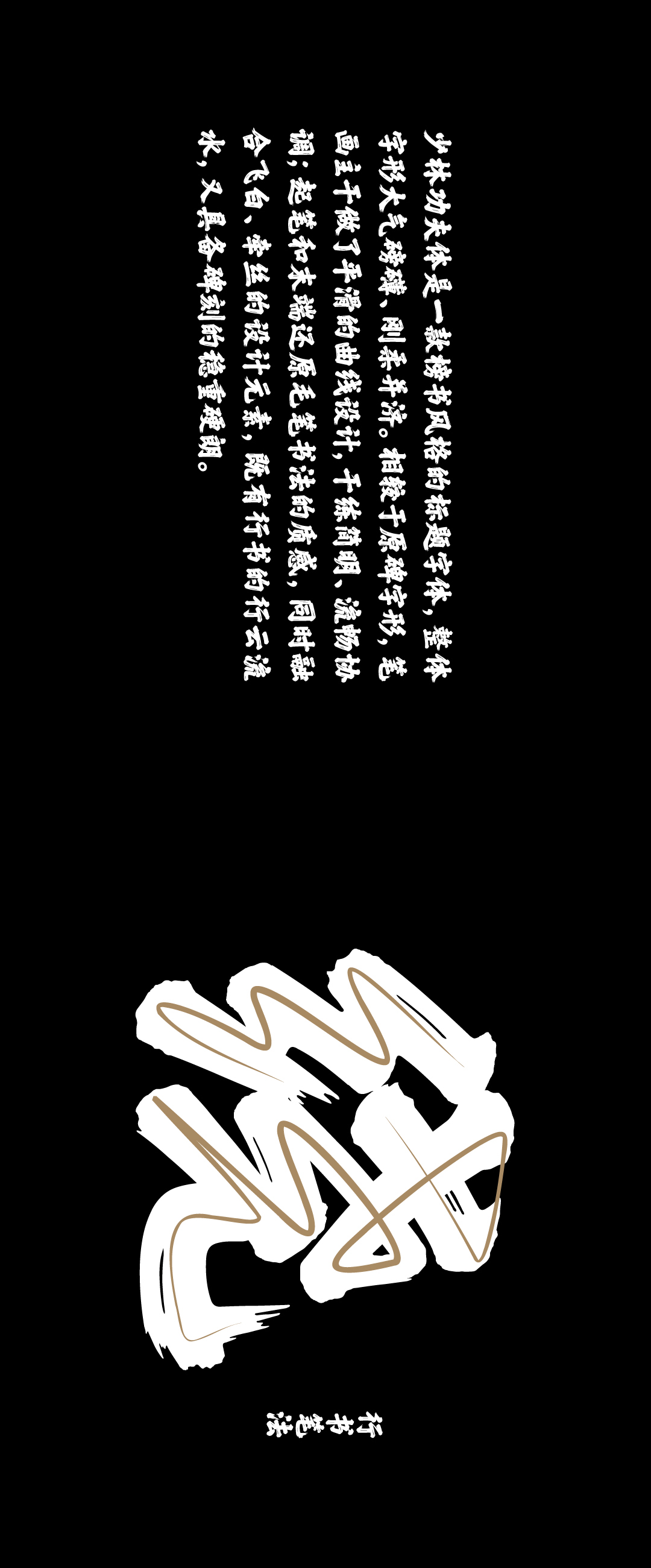
方正少林功夫体
方正少林功夫体,来源于少林寺的“千崖万壑”碑。在字体设计中,将笔画主干的部分做了平滑的曲线设计,干练简明;笔画的起笔和末端,还原了毛笔书法的质感,同时融合了飞白牵丝的设计元素,让方正少林功夫体不仅具有石刻的硬朗朴素,也同时具有毛笔字的细节和情绪。该字体字形大气磅礴,刚柔并济,既有行书的行云流水,又具备碑刻的稳重硬朗,与少林功夫的形象完美融合。方正少林功夫体是多语言文种的超大字库,计划开发:中文简体、中文繁体、BIG5繁体、日语、韩语、拉丁、希腊、西里尔、阿拉伯等多个语种。不同的语言文字,有着不同的书写习惯和审美传统,在设计中既兼顾了各语言文种的特点,又保持了整体风格的统一。”
设计师:汪文、陈宇、何诗旸(拉丁及小语种)
字体设计团队
主创设计师
汪文,陈宇,何诗旸
主要制作人员
李泽曦,齐兴城,郭毓海